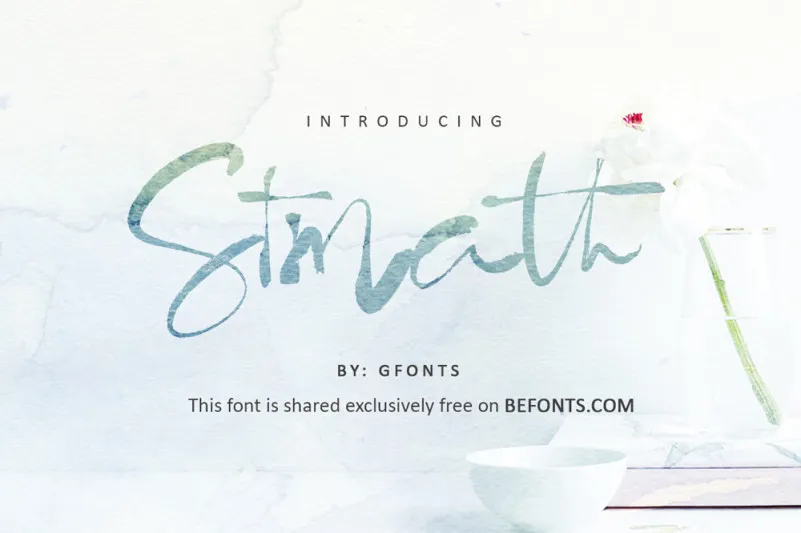
Stmath Calligraphy Font – Fonte Grátis
Stmath Calligraphy Font
A Stmath Calligraphy Font é uma criação moderna que se destaca por seus finos tracinhos ao subir e seus tracinhos pesados ao descer, inspirada na escrita moderna de calligrafia. Desenvolvida com a técnica do traçado de canetas sobre tinta, essa fonte tem um toque especial em cada letra que é cuidadosamente moldado para dar vida aos teus projetos de design. Perfeita tanto para criações de site moderno quanto para assinaturas de evento, embalagens e materiais de wedding stationery, a Stmath Calligraphy Font oferece uma beleza sofisticada e elegante que vai ao encontro do seu estilo único. É um recurso indispensável para designers que buscam tornar seus projetos ainda mais artísticos e chamativos.
Designer: Gfont